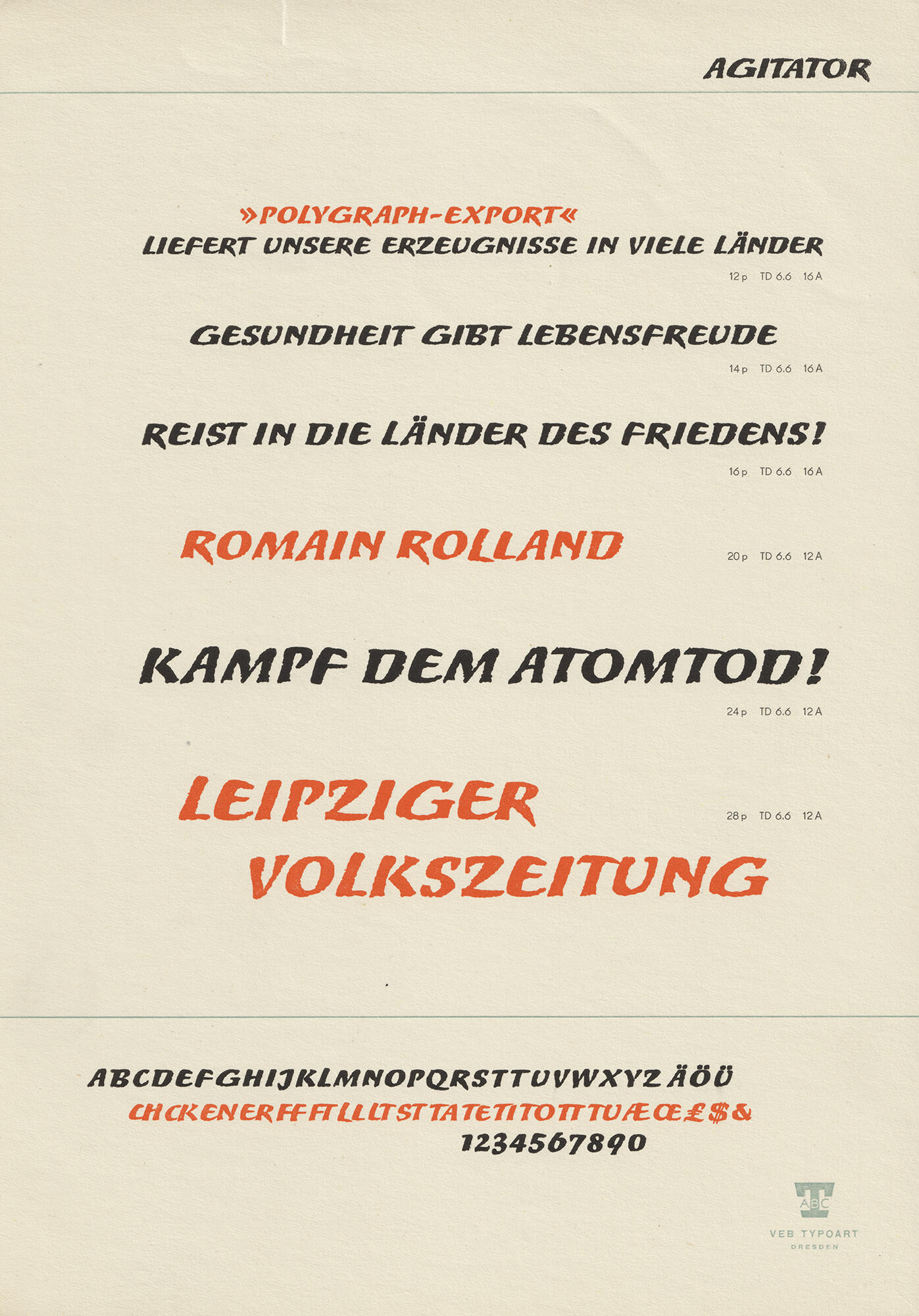
Wolfgang Eickhoff wurde 1914 in Düsseldorf geboren und war Dozent für Schrift an der Fachschule für angewandte Kunst Berlin.
Die ursprünglich bei Typoart erschienene Agitator gibt es als Digitalisierung unter dem Namen Merc von Canadatype.
Originalmuster von Typoart
Digitalisierung von Canada Type